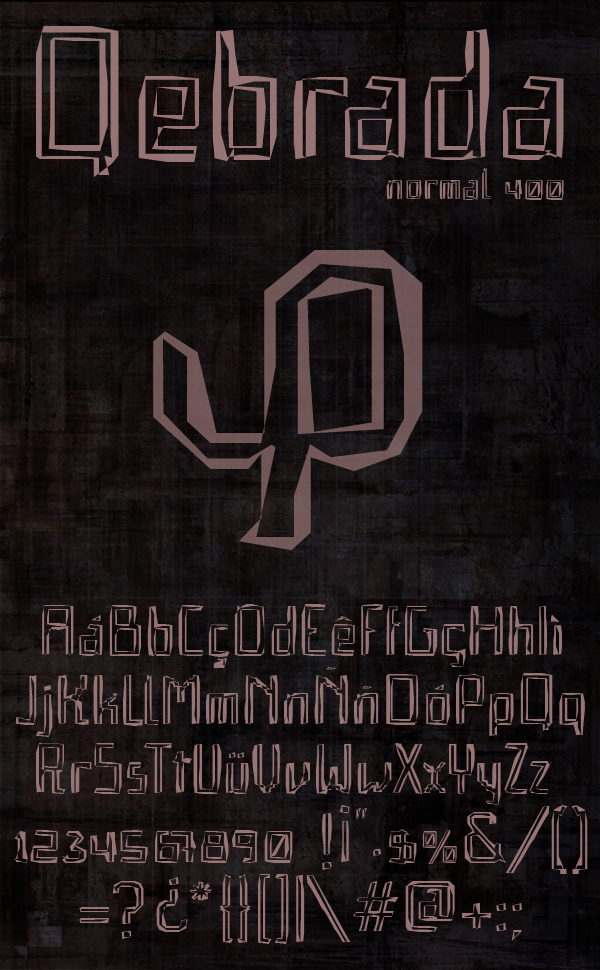
Qebrada
Esta fuente es un experimento de deconstruccin hecho a partir de un nuevo proyecto tipogrfico en el que trabajo basado en la secuencia de Fibonacci y Lucas. La fuente dispone de todos los caracteres latinos, opciones Open Type y Kerning. http://defharo.com/fonts/descargar-fuentes-gratis/
Esta fuente está basada, en sus proporciones, en la secuencia de fibonacci, la secuencia de Lucas y el triangulo de Kepler. Soy deFharo diseñador freelance en Spain, visita mi web defharo.com